64 خطًا رائعًا تريد استخدامها في عام 2023
نشرت: 2023-04-21قال أحد المصممين من ThoughtWorks ذات مرة ، "عندما تكون الطباعة على النقطة ، تصبح الكلمات صورًا." وبالفعل ، كان شون لوكاس على حق.
التصميم الجرافيكي هو العنصر الأساسي الذي يجذب الانتباه ، وكذلك الخطوط الرائعة. عند اختياره بشكل مناسب ، سواء كان خطًا مخصصًا أو مجانيًا ، فإن اختيار الخط سينقل الرسالة الصحيحة. عندما يعرض المرء الخطوط وتصميم الرسوم النجمية ، توقع جذب المزيد من مؤيدي العلامة التجارية. لماذا؟
وفقًا لـ Engadget ، هناك ثمانية أسباب تجعل الخط ، أو الطباعة بشكل عام ، هو نهاية كل شيء في التسويق.
- يتواصل مع جمهورك
- يجذب القراء
- يحافظ على انتباه الجمهور
- يثير بعض الحالات المزاجية والمشاعر
- يؤسس الهيكل
- يخلق تناغم التصميم
- ينضح بالاحتراف
- يؤسس السلطة
لذلك عندما تفكر في خطوط حصرية لإبراز تصميماتك أو شعاراتك ، تأكد من أنها قريبة من هويتك وصورتك. دعنا ننتقل إلى المطاردة ، ودعنا نعرض لك 64 خطًا رائعًا لبناء التعرف على العلامة التجارية.
خطوط SERIF الرائعة
1. Fakedes بواسطة سيريل ميخائيلوف
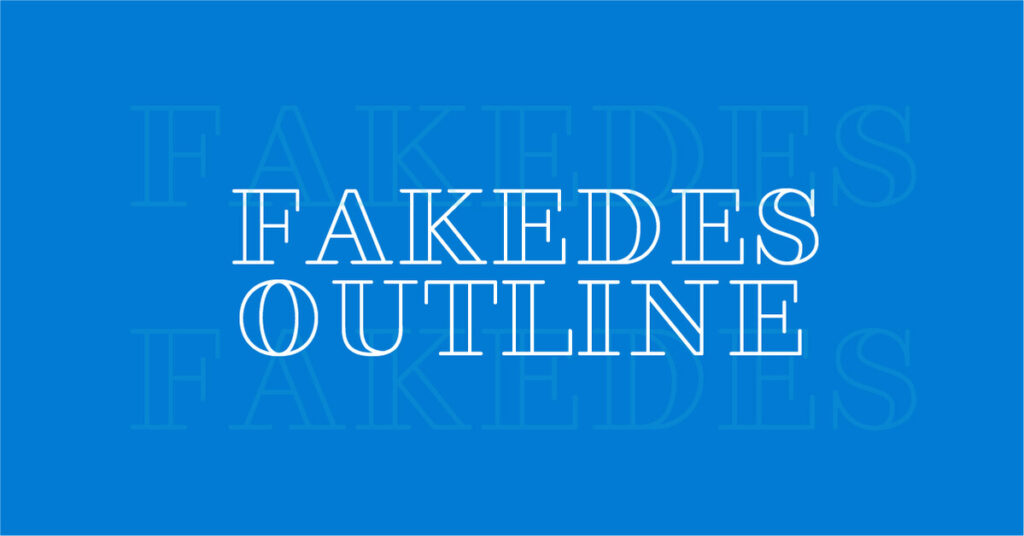
نظرًا لطبيعته المستديرة النظيفة والخطوط المزدوجة ، يعد Fakedes خطًا رائعًا ممتازًا للعناوين.
2. منتدى من قبل دينيس مشاروف
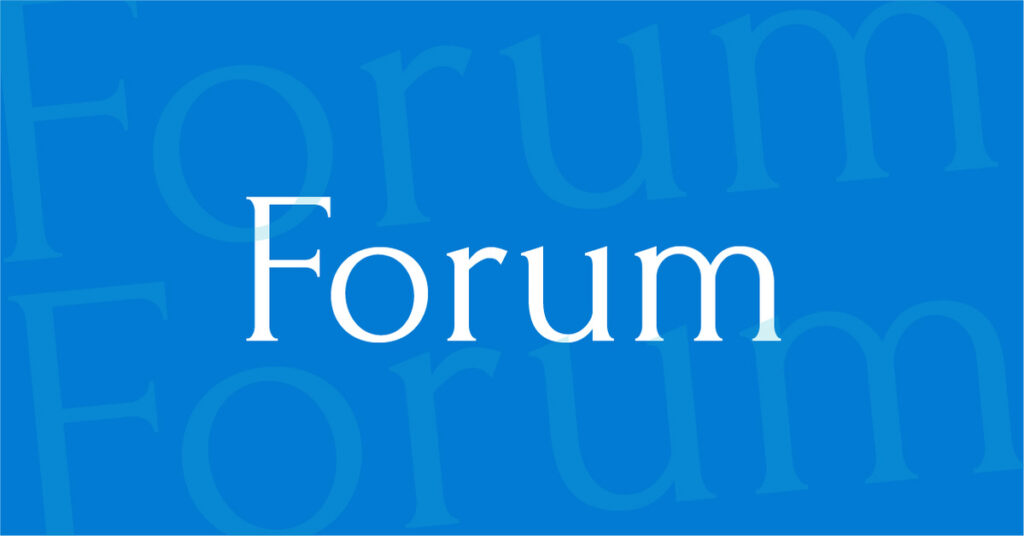
هذا الخط الرائع ، Forum ، يذكرنا بكتاب روماني قديم خلال الإمبراطورية الرومانية ، مع لمسة عصرية.
3. موتشاشو لجيف شرايبر
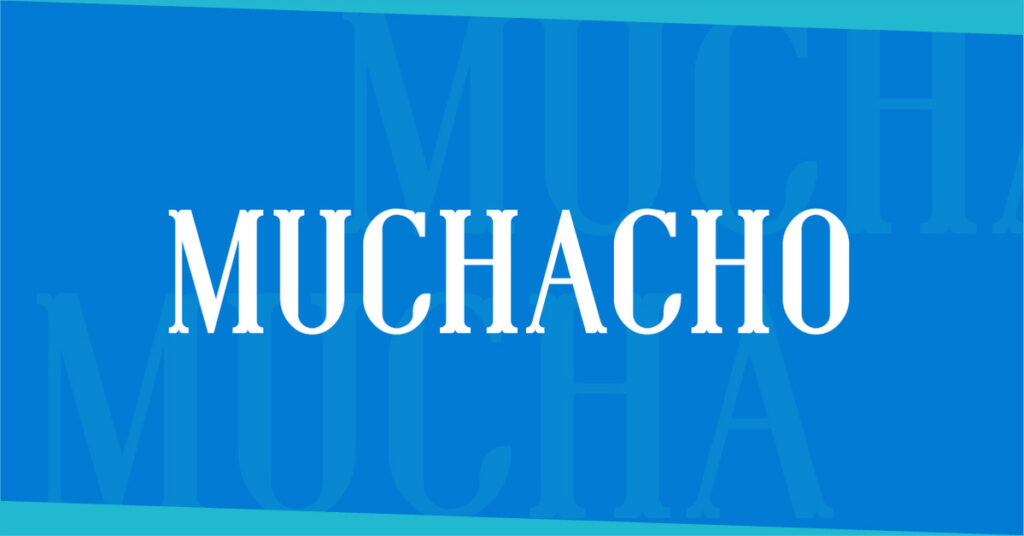
هذا الخط الرائع ينضح بأسلوب قديم. نظرًا لأنه خط ذو أحرف استهلالية كاملة ، فإن هذا النمط مثالي للعناوين أو العناوين.
4. باربارو ويسترن بواسطة إيفان نونيز
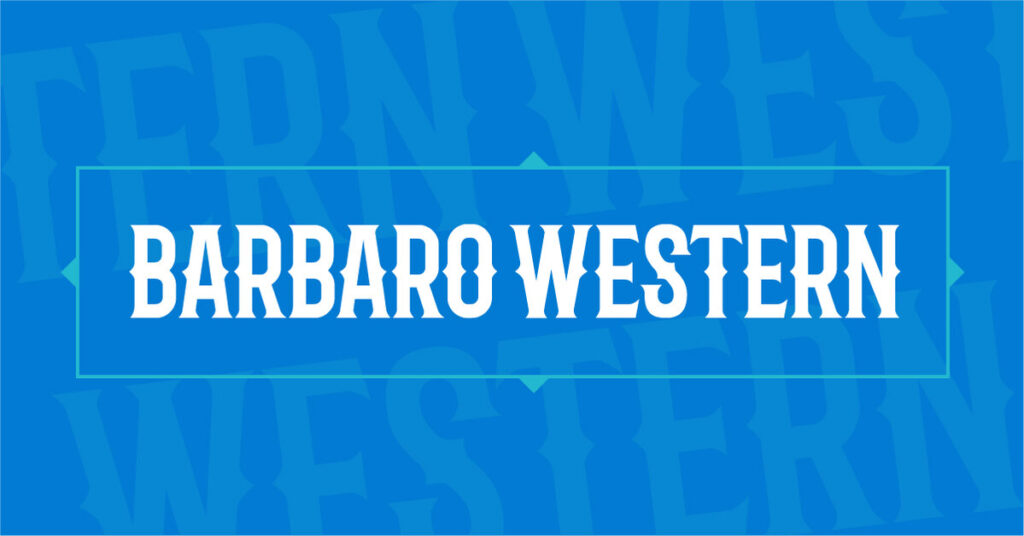
إذا كنت تريد أن تشعر قليلاً من Wild Wild West بتصميماتك ، فإن Barbaro Western هو حديث وشهم.
5. Le Super Serif من SuperBruut
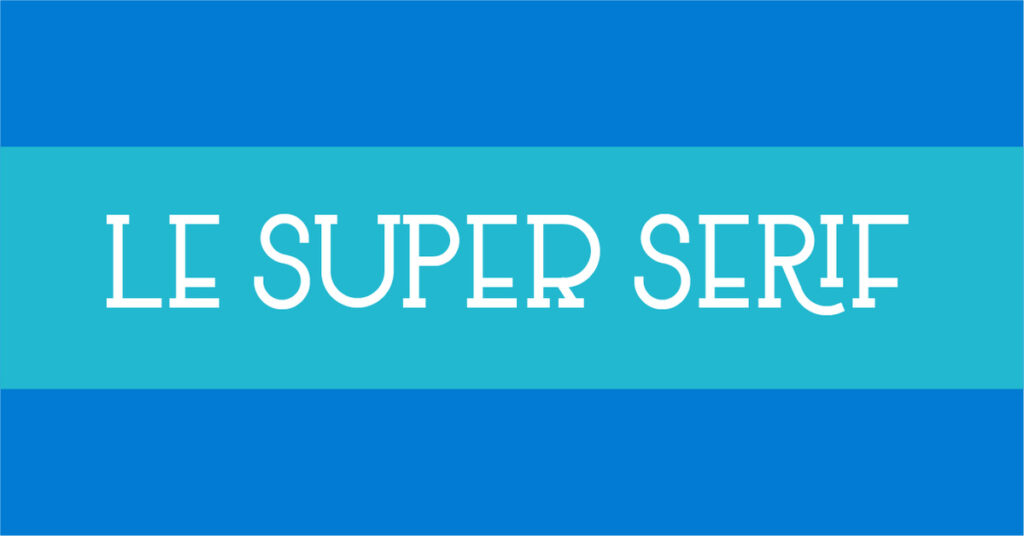
هذا الخط فريد ومميز ينبثق عن الأسلوب والفئة. يمكنني تقريبًا رؤيته على نوافذ بوتيك الأزياء ، حيث أبيع فساتين راقية.
6. لوفاتو لايت بواسطة فيلاتيب
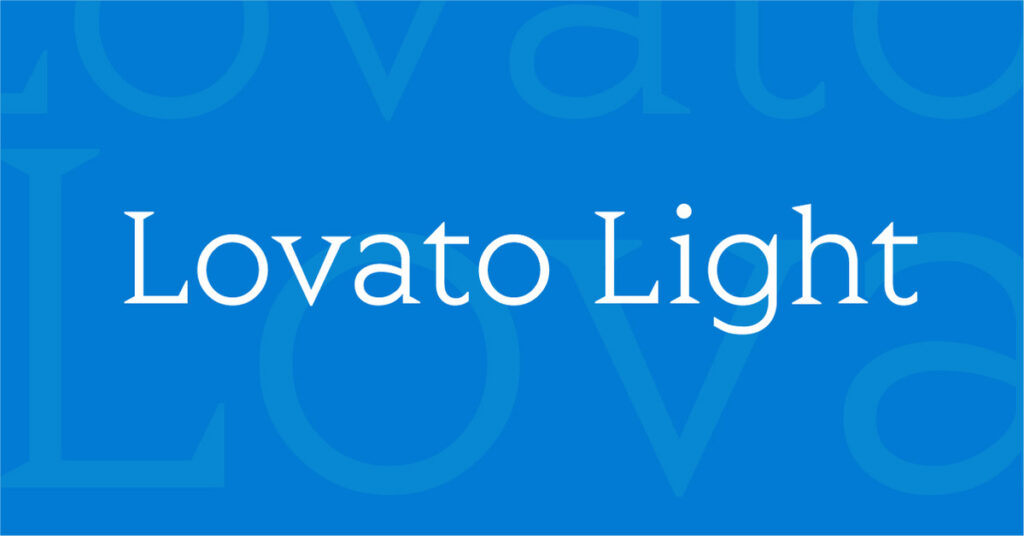
للحصول على خط رقيق أكثر ذوقًا ومباشرة ، يعد Lovato Light الخيار الأمثل. إنه منعش ويخلق جاذبية منظمة.
7. فالكيري بواسطة هندريك رولانديز
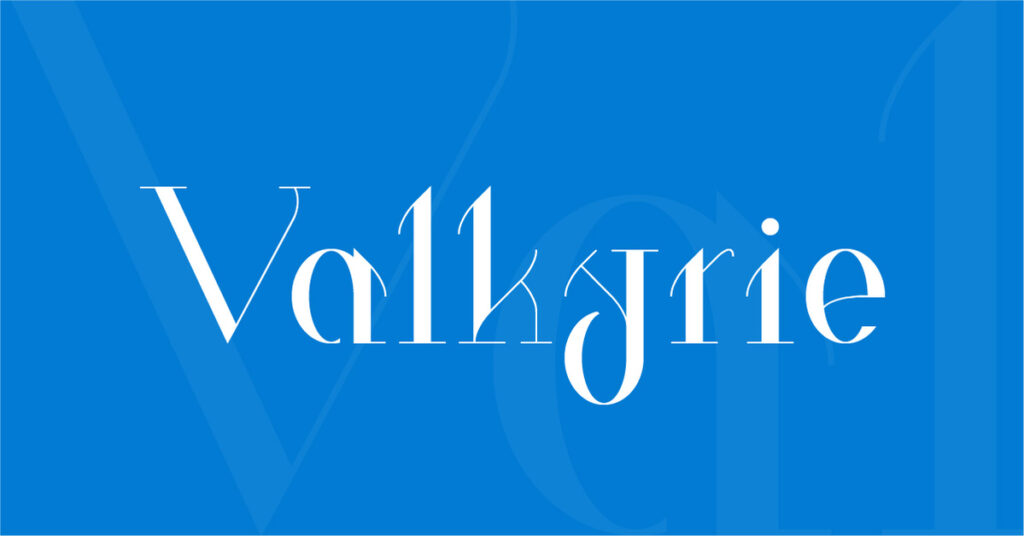
تتضمن الخطوط الرائعة لكمة تجعل تصميماتك بارزة. أحد الأمثلة على ذلك هو خط Serif المرح ، Valkyrie.
8. بالاسيو بواسطة ناثان طومسون
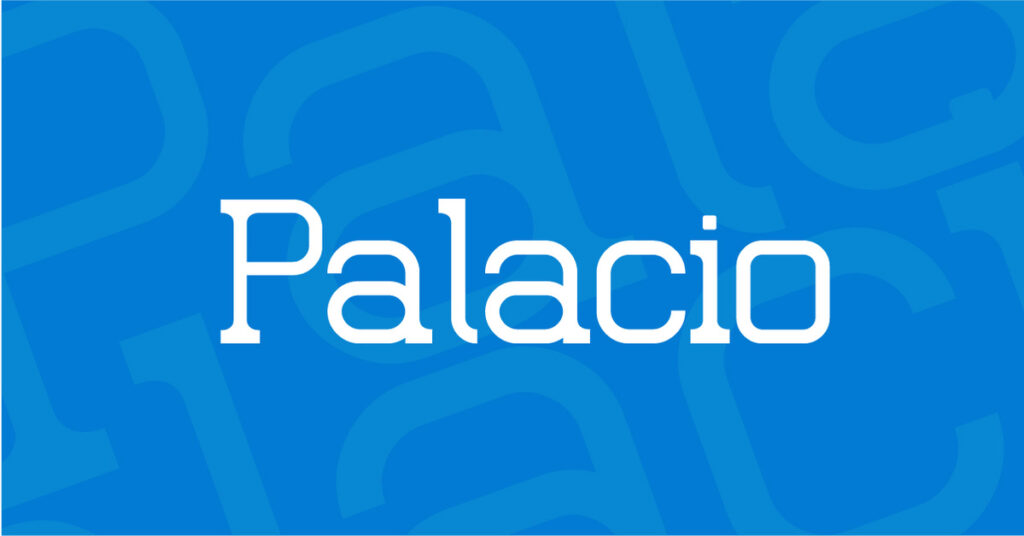
من يقول أن التقليد والمعاصر لا يختلطان؟ يعتبر خط Palacio رائعًا بما يكفي لتصميماتك الحديثة ، ولكنه تم تجريده إلى مظهر تقليدي جميل.
9. Blnc بواسطة Swist'blnk
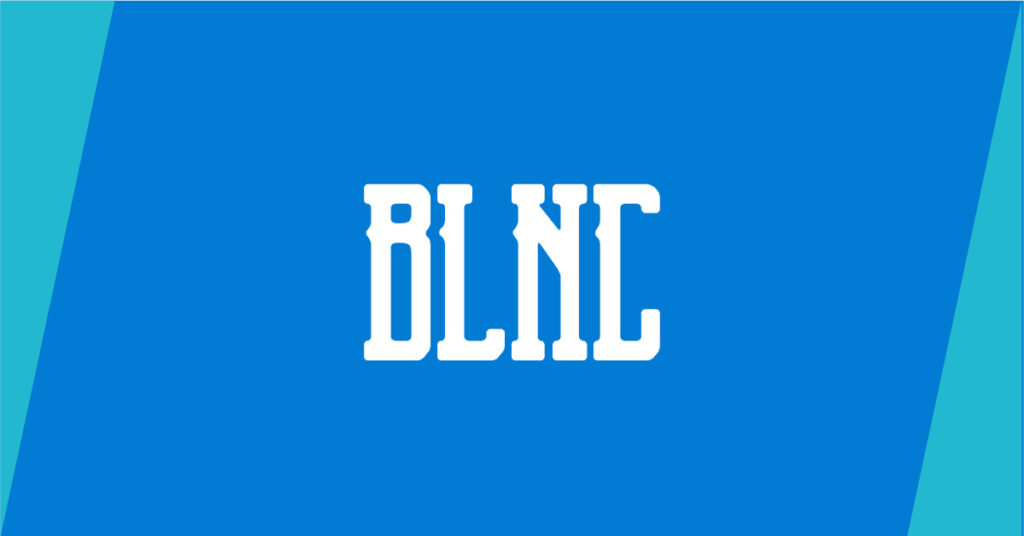
خط آخر رائع بأسلوب غربي قديم هو Blnc. إنها مناسبة لأي شيء مطبوع أو رقمي تقريبًا.
10. مودوم لجوناثان هيل
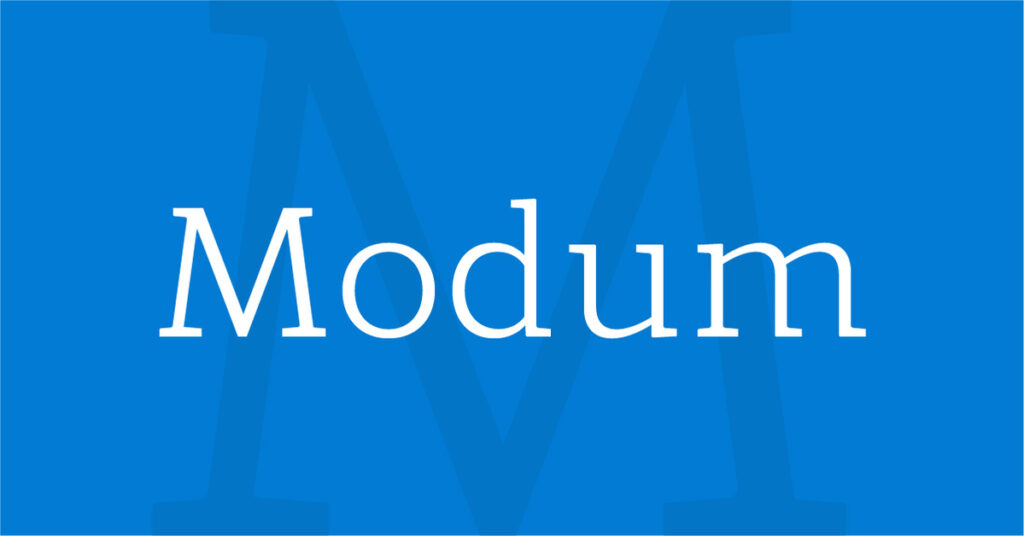
تخلق جماليات خط Modum المستديرة مظهرًا وديًا وعصريًا ، مما يجعلها لطيفة وراقية.
11. كتاب الثقاب لسيمون ووكر
هذا الخط الممتاز يصرخ بالغرب والرجولية مناسب لعناوين مشروعك. نمط serif ممتد قليلاً ، مما يجعل الخط أكثر بروزًا.
12. Kawoszeh من GLUK
ما يجعل الكووسة خطًا مذهلاً لاستخدامه في أي تصميم هو ضرباته الدقيقة والحساسة التي لا مثيل لها.
13. بوبر بقلم ديمتري جولوب
بالنسبة لعناوين التصميم الخاصة بك ، لا شيء يمكنه التغلب على تفرد خط Bobber. إنها جميع الأغطية والألواح.
14. المتأنق من قبل دان Gneiding
إذا كنت تعتقد أن رعاة البقر رائعين ، فإن نمط الخط هذا سوف يناسب كل ما تبذلونه من المرح والتصاميم الإبداعية ، مع لمسة من الأجواء الغربية القديمة.
15. شوبلين برينيه بيدر
أسلوب خط Choplin بسيط ومحايد. تعتبر Choplin ذات الوزن الغامق مناسبة أيضًا للملصقات أو أي وسيلة طباعة تسويقية. إنه حتى خط قابل للقراءة على الويب أيضًا.
خطوط SANS SERIF الرائعة
16. أركاديا من قبل مانه نجوين
يمكن أن تسير مشاريع التصميم الأنثوية جنبًا إلى جنب مع هذا الخط الأنيق والبلاستيك بلا خط.
17. ستيج بواسطة أليكس هيدين
يذكرني Stig بسيارة قوية بقوة حصانية مثل سيارة فيراري. إنه نظيف ، كلاسيكي ، لكنه ديناميكي.
18. كوليكو من Fontfirma
معلمة بأشكال هندسية ، يحتوي خط Koliko على أحرف من اللغات السلافية.
19. Rometric بواسطة توماس ريتشاردسون
هذا الخط الفني يسكن في الهندسة والخطوط. عندما يتم نسج كلاهما معًا ، تكون النتيجة هذا الخط الفريد ، والمثالي للتصميمات الجديدة والكلاسيكية.
20. سيرتا بلا بقلم غلين جان
بسيطة لكنها مؤهلة ، يمكن لـ Certa Sans أن تجعل جميع تصميماتك تنبض بالحياة. كما أنه يضيف لمسة عصرية إلى أي طباعة أو رسومات بشكل عام.
21. رالف بواسطة راليف
تظهر بعض الأحرف في هذا الخط بانحراف ، مما يجعل خط Ralev sans serif بارزًا.